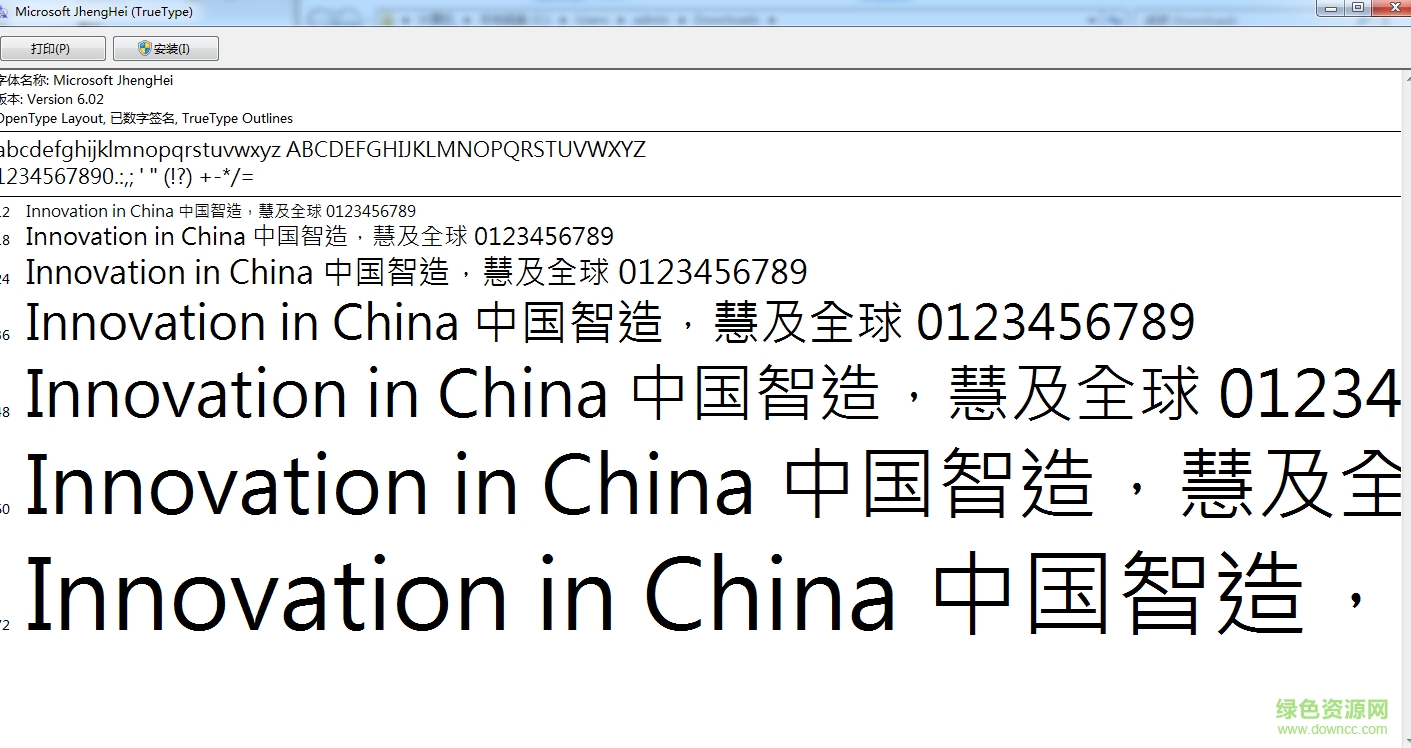
microsoft jhenghei light 超亮
microsoft jhenghei light字體又叫微軟正黑體,筆畫(huà)簡(jiǎn)潔,閱讀性強(qiáng),該字體放大依舊很清晰,屏幕顯示效果良好,需要的小伙伴快來(lái)下載收藏吧!
microsoft jhenghei字體介紹
微軟正黑是由微軟公司為其新一代操作系統(tǒng)Vista開(kāi)發(fā)的實(shí)用性中文字體。該字體將作為Vista中國(guó)臺(tái)灣地區(qū)的默認(rèn)字體,以支持高清顯示的ClearType功能。
微軟正黑和微軟雅黑不同
對(duì)于微軟雅黑和微軟正黑,不好簡(jiǎn)單的用簡(jiǎn)體或者繁體來(lái)區(qū)分他們,因?yàn)檫@兩套字體都同時(shí)包含了比較完整的簡(jiǎn)繁體漢字,以確保在簡(jiǎn)體和繁體混排的頁(yè)面上都能夠完美的顯示。但由于兩岸的文教部門(mén)在各自的文字規(guī)范中對(duì)漢字的寫(xiě)法規(guī)定有很多細(xì)節(jié)上的不同,所以這兩套字形在正式場(chǎng)合是不能混淆使用的。同樣的,日文的Meiryo字體中也包含了大量的繁體漢字,不過(guò)由于漢字在日本也經(jīng)過(guò)了上千年的演變,日文中的漢字寫(xiě)法和中國(guó)大陸和臺(tái)灣也有著相當(dāng)?shù)膮^(qū)別。